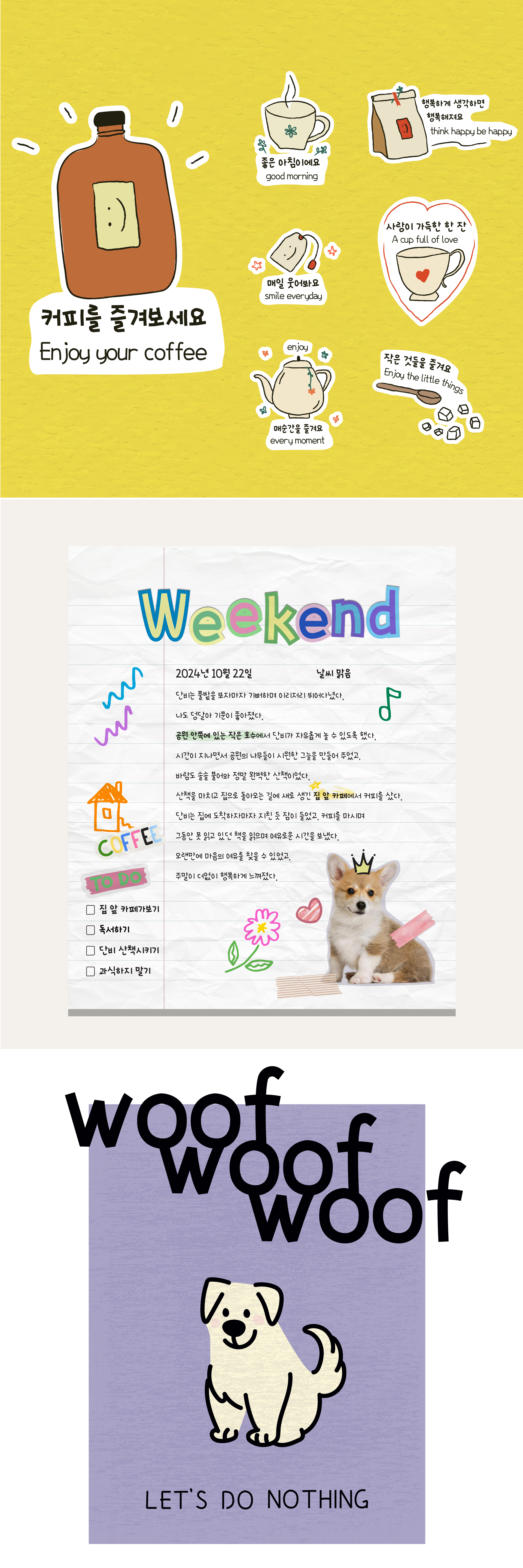
'끄적끄적' 폰트는 손으로 끄적이는 듯한 느낌의 서체입니다. 글자들이 일렬로 정렬되지 않고 약간 기울어지거나 흐트러진 모습으로 배열되어, 전체적으로 자유롭고 개방적인 분위기를 연출합니다. 이 폰트는 감성적인 글이나 일기, 또는 손글씨의 따뜻함을 필요로 하는 디자인에 탁월합니다.